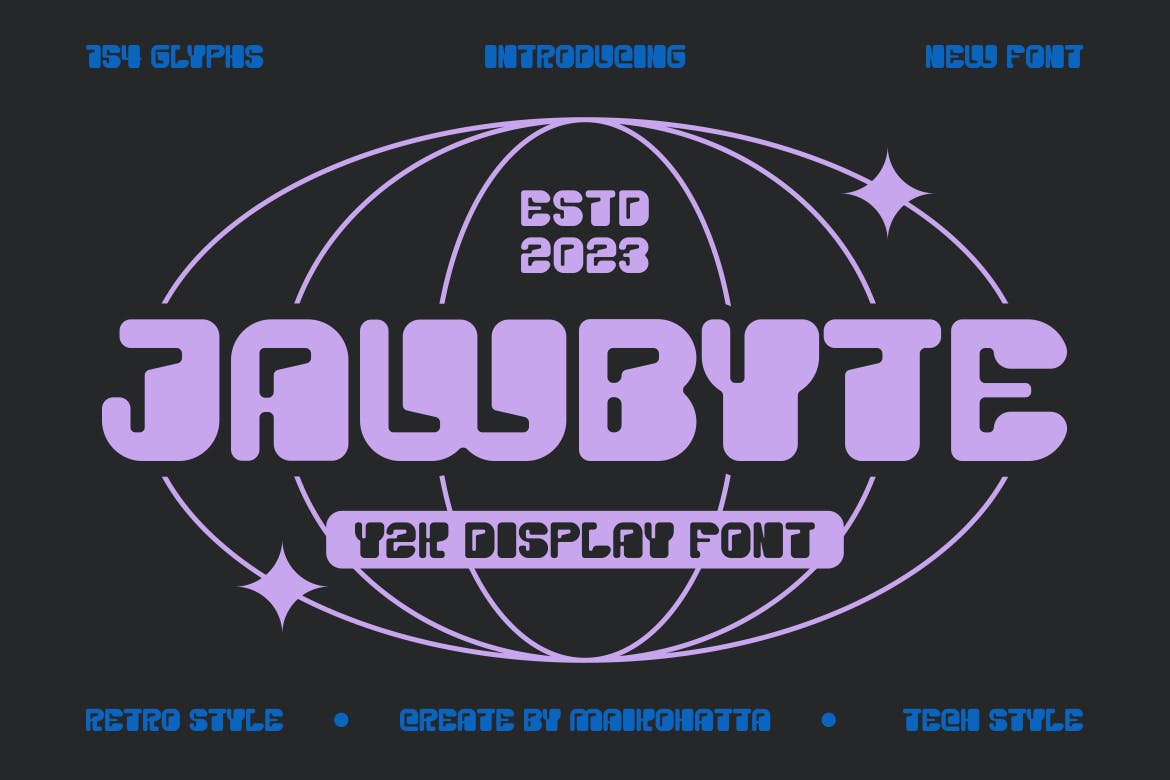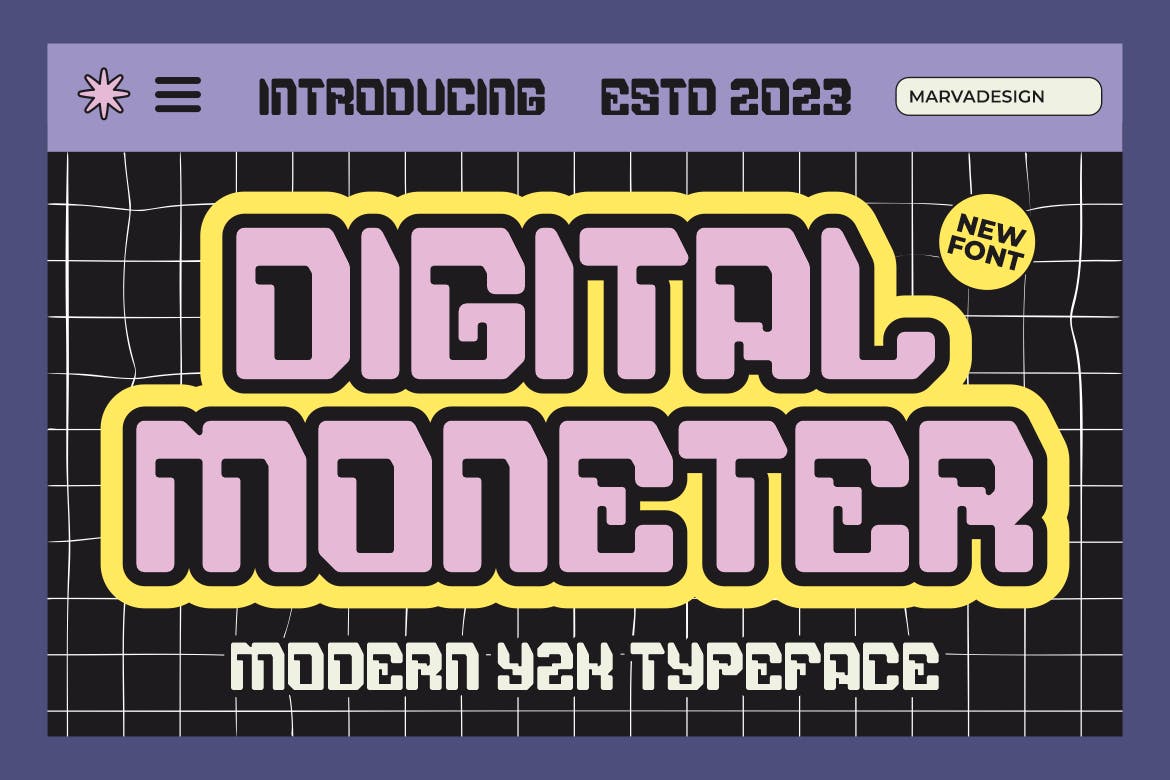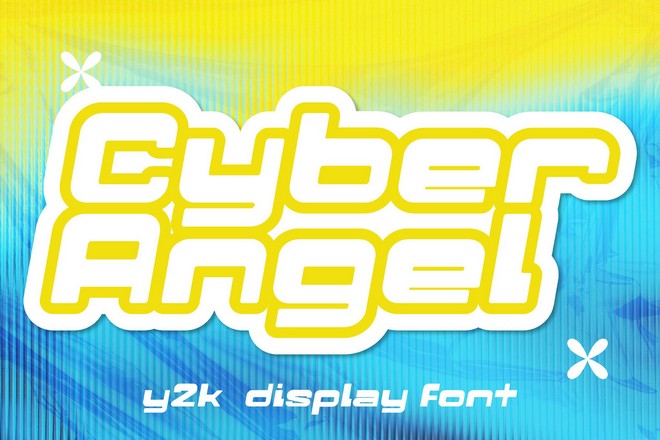
25+ Font Y2K dan Tahun 2000 Terbaik
Hari ini, kami menyoroti font Y2K terbaik yang menangkap esensi era ikonik evolusi teknologi ini. Baik Anda ingin menambahkan kesan futuristik atau nostalgia ke masa lalu, beragam perpaduan font Y2K kami pasti akan menginspirasi.
Di sini, Anda akan menemukan font yang menangkap esensi getaran fantasi fiksi ilmiah yang dinamis untuk menambahkan tampilan tahun 2000-an pada desain Anda. Font-font ini adalah cara untuk membawa pemirsa Anda ke era di mana dunia digital dan fisik mulai kabur, membuka babak baru dalam estetika desain.
Digibit – Font Y2K Modern
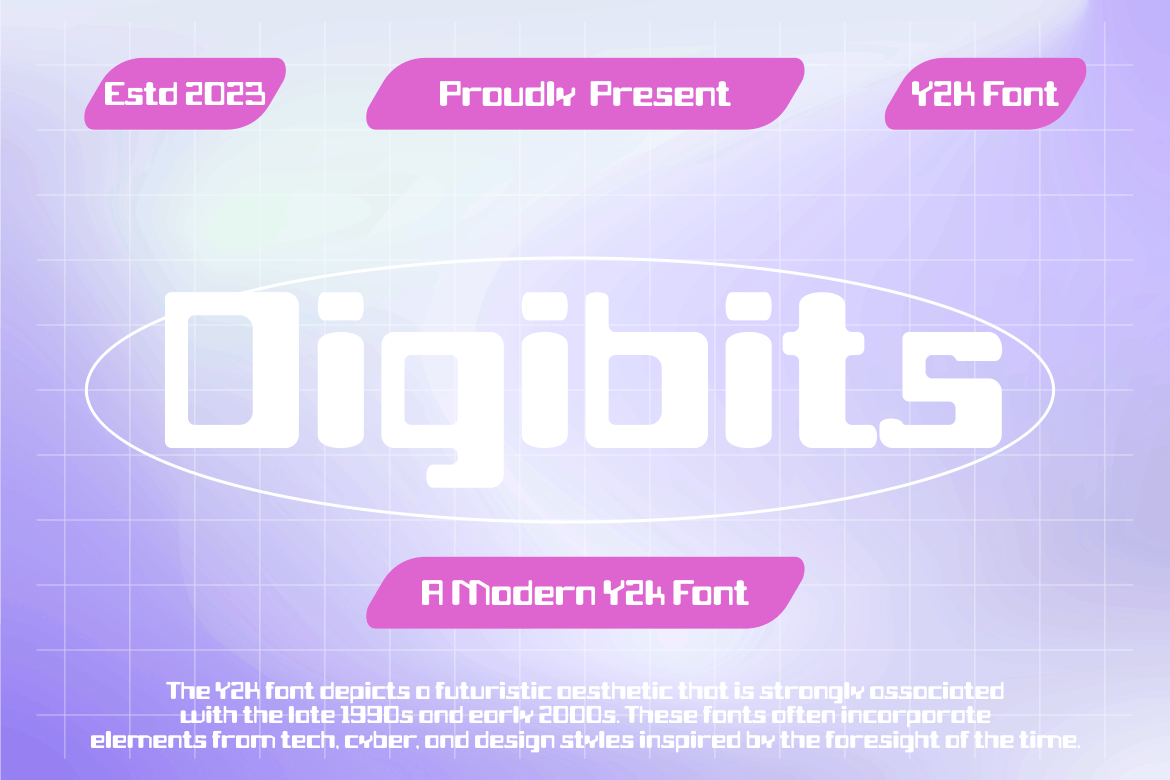
Digibits adalah font Y2K yang menangkap tampilan dan nuansa ikonik estetika teknologi awal tahun 2000-an. Font unik dan futuristik ini mencakup elemen seperti tampilan komputer lama, neon, piksel, dan bentuk geometris yang mencerminkan permulaan era digital. Dengan huruf besar dan kecil tersedia dalam format otf dan ttf, Digibits adalah pilihan sempurna untuk desain retro yang berani.
Bavose – Font Gelembung Y2K
Font gelembung Y2K ini menjanjikan menghadirkan ledakan masa lalu ke setiap desain, mengubah visual Anda dari biasa menjadi luar biasa. Nostalgia tidak pernah terlihat sekeren font bergaya jadul ini. Ini sempurna untuk menambahkan getaran teknologi retro klasik ke desain grafis Anda.
BELANDA – Font Retro Y2k
Font HOLANDA mencerminkan visual awal tahun 2000-an. Desainnya merupakan perpaduan elemen seperti tampilan komputer lama, piksel, neon, dan bentuk geometris yang sangat mencerminkan kemajuan teknologi di era tersebut. Tersedia dalam format otf dan ttf, font huruf besar ini adalah cara ideal untuk menanamkan sedikit nostalgia futuristik ke dalam proyek kreatif Anda.
Cyber Angel – Font Y2K 2000
Cyber Angel adalah jenis huruf dinamis yang membangkitkan getaran inovatif era digital tahun 2000an. Ini menampilkan teks sans-serif yang ramping dan tebal, menangkap rasa nostalgia dan energi berpikiran maju. Ideal untuk desainer yang ingin menambahkan sentuhan fiksi ilmiah ke proyek mereka, font ini menyempurnakan situs web, logo, atau label produk dengan sentuhan futuristik yang menawan.
Cytone – Font Y2K 2000
Cytone adalah font yang terinspirasi Y2K yang menghadirkan sentuhan futuristik pada proyek kreatif Anda. Ideal untuk tema berbasis teknologi atau galaction, tipografi serbaguna ini dapat menjadi tambahan yang menarik untuk film, logo, poster, permainan, dan buku. Merangkum suasana musik dan budaya pop awal tahun 2000-an, Cytone adalah aset yang mudah digunakan, dan hadir dalam format otf dan ttf.
Espero – Font Tampilan Y2K
Espero adalah jenis huruf yang mencolok secara visual yang mencerminkan estetika Y2K. Ini menyalurkan gaya futuristik dan kemajuan teknologi di awal tahun 2000-an, dengan mengacu pada tampilan komputer lama, pikselasi, neon, dan bentuk geometris. Tersedia dalam format otf dan ttf, menampilkan karakter huruf besar dan kecil dan mendukung berbagai bahasa.
Mescio – Font Gelembung Y2K
Lihatlah Mescio, koleksi jenis huruf bertema retro yang cocok bagi mereka yang ingin menanamkan kreasi modern mereka dengan nostalgia awal tahun 2000an. Ideal untuk artis indie, produser musik, atau desain poster, Mescio membawa Anda kembali ke era musik pop dan lampu neon.
Punk Cyber – Font Retro tahun 2000-an
Benamkan diri Anda dalam pesona retro tahun 2000-an dengan Punk Cyber, font yang terinspirasi Y2K. Mengingat estetika zaman yang dinamis dan berani, font kreatif ini menawarkan enam gaya unik termasuk Regular, Slant, Outline, Extrude, Outline Slant, dan Extrude Slant. Baik Anda mendesain untuk media sosial, branding, atau media cetak, Punk Cyber akan menambahkan keunggulan tersendiri pada kreasi Anda.
Pembuat Sampah – Font Y2K Modern
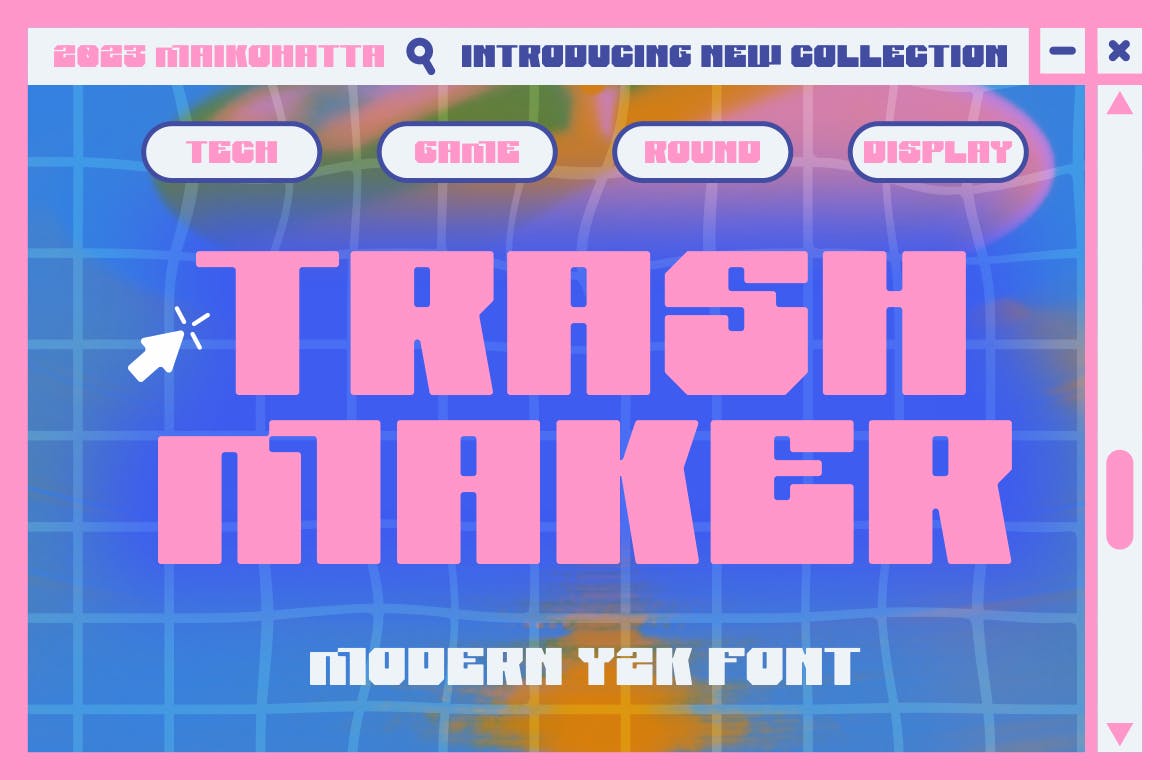
Lihatlah Trash Maker, jenis huruf menyenangkan dan futuristik yang merangkum estetika digital awal tahun 2000-an. Ini mengambil inspirasi dari fitur ikonik pada masa itu, seperti tampilan komputer lama, piksel, neon, dan bentuk geometris. Tersedia dalam huruf besar dan kecil, font multibahasa ini hadir dalam format otf dan ttf.
Remock – Font Retro Gelembung Y2K
Ambil perjalanan desain Anda kembali ke pergantian milenium dengan font Remock. Font tampilan autentik ini, tersedia dalam format otf dan ttf, cukup serbaguna untuk berbagai proyek branding, termasuk logo dan desain produk. Menawarkan pilihan huruf besar, huruf kecil, dan multibahasa, memastikan presentasi yang luar biasa dalam beragam konteks.
Calpina merupakan font bergaya Y2K yang memiliki desain huruf yang terinspirasi dari tahun 2000-an. Font ini menampilkan desain surat yang bersih dan sederhana yang sangat cocok dengan poster, pamflet, dan postingan media sosial Anda. Ini gratis untuk penggunaan pribadi.
Dojebi – Font Y2K 2000 Gratis
Anda dapat menggunakan font ini secara gratis dengan proyek pribadi dan komersial Anda. Ini memiliki karakter bergaya Y2K yang akan membuat teks dan judul Anda menonjol dari yang lain. Perhatikan bahwa font hanya menyertakan karakter huruf kecil.